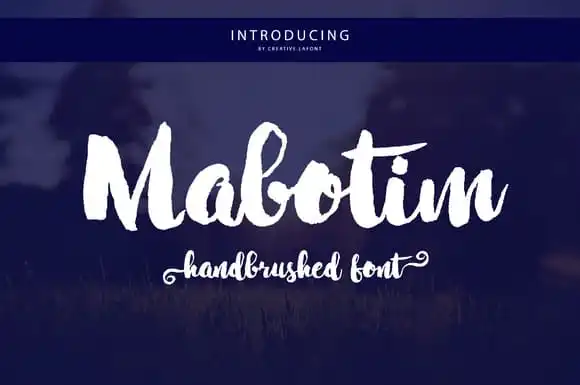
Mabotim Brush Font – Download Grátis
A Mabotim Brush Font é uma letra curva, divertida e moderna, combinando elementos do desenho à mão com letras fortes. Suas formas leves e elegantes fazem dela um recurso versátil para várias finalidades. Ideal para revistas, embalagens, títulos, outdoors, camisetas, logotipos, citações, cartões de convite, roupas de casamento, anúncios, adesivos em imagens e páskais na web. Com seu estilo natural e aparentemente descontraído, a Mabotim Brush se destaca como uma opção para aqueles que buscam algo único e autêntico. A fonte foi criada por Creative.lafont, um designer conhecido por suas letras que transmitem a essência de cada projeto, seja em design gráfico ou tipográfico. Sem dúvida, ela é perfeita tanto para trabalhos profissionais quanto para criações artísticas e pessoais, fornecendo uma opção divertida e única para quem busca algo diferenciado em seu trabalho visual.